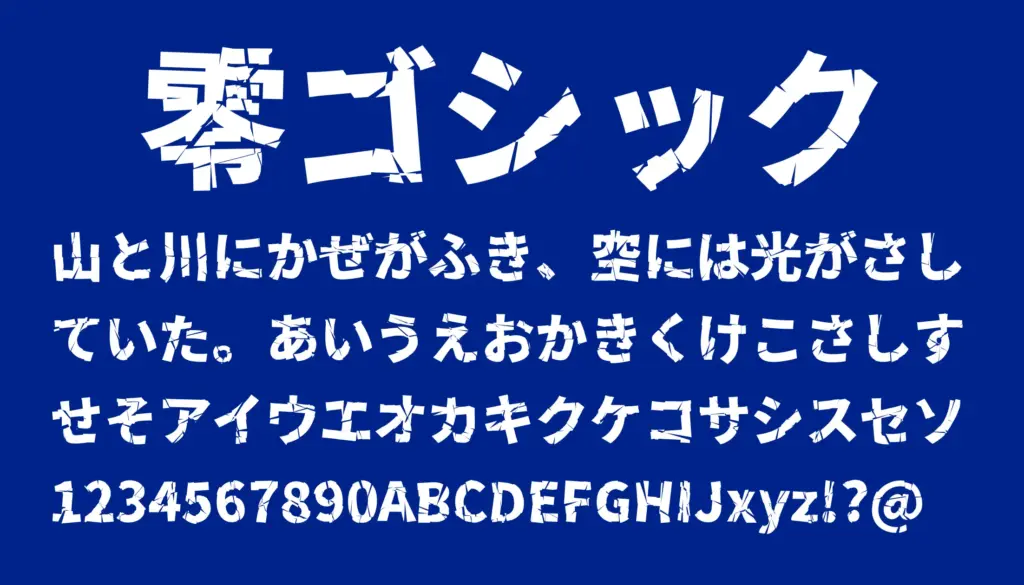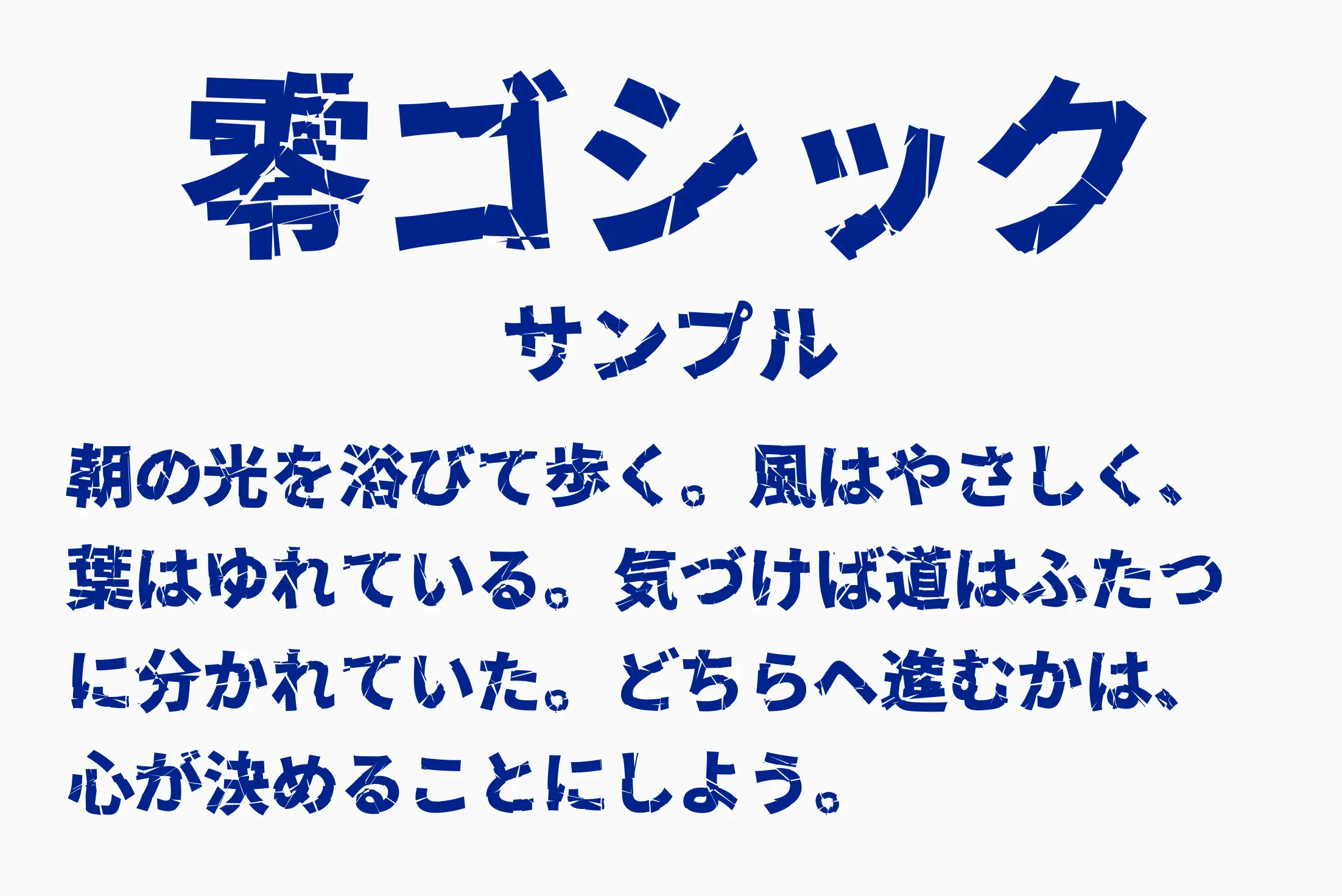
近未来的で無機質な印象をもつミニマル&直線的なゴシック体です。
縦横の線幅がほぼ均一で、角も直角的。サイバー感やインダストリアルな雰囲気を演出できるフォントです。読みやすさを保ちながらも、無機質・冷静・近未来といった世界観をデザインに与えることができ、ゲーム、SF作品、映像系サムネイル、ロゴ制作などに適しています。
零ゴシック